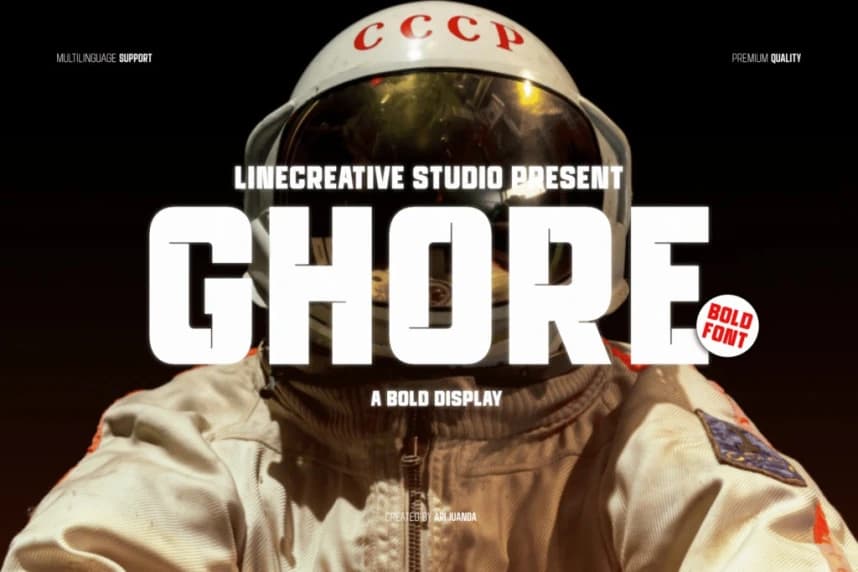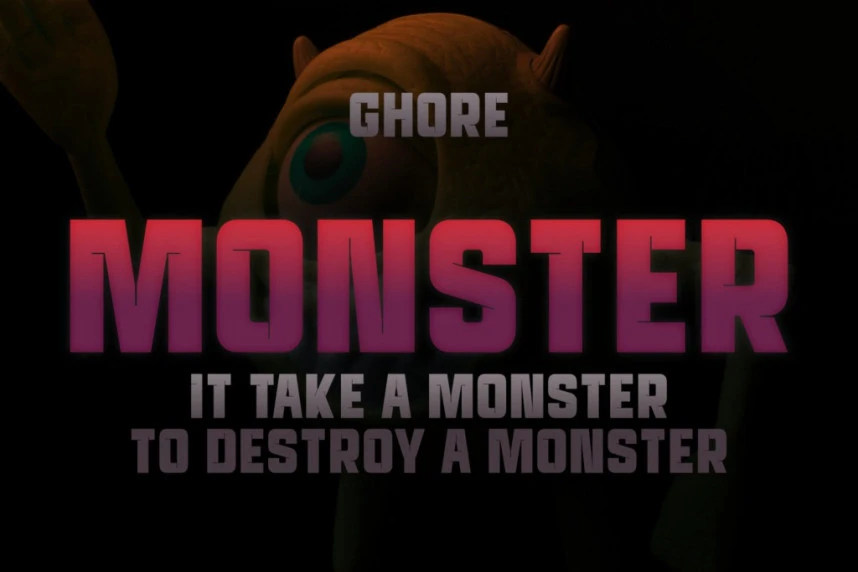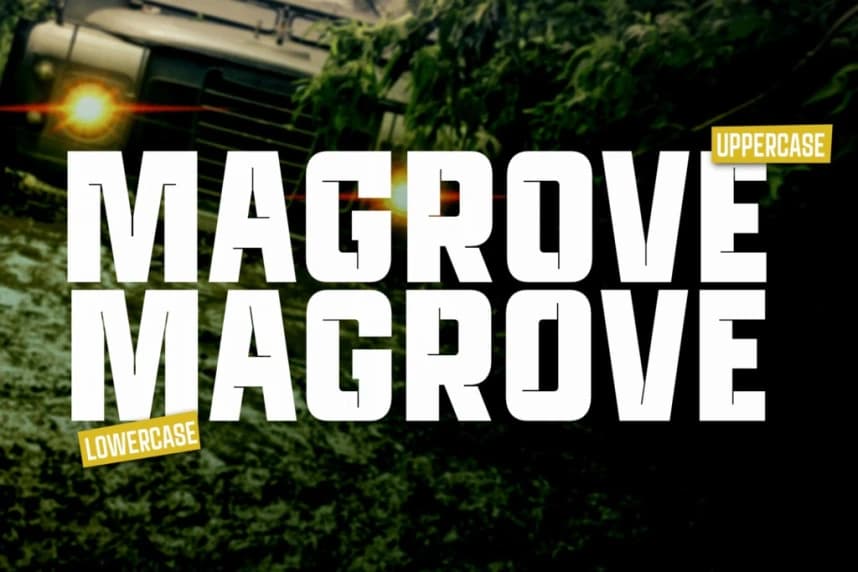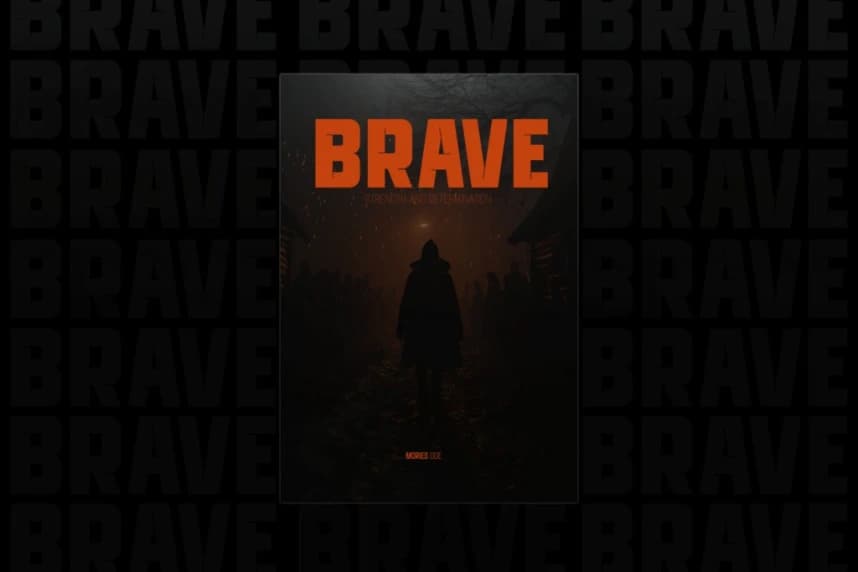
Ghore Font
Ghore Font! Modern bir sans display yazı tipi, kalın bir stile sahip; font gövdesinin her köşesinde bulunan kesik oluklar ona keskin ve fütüristik bir görünüm kazandırıyor.